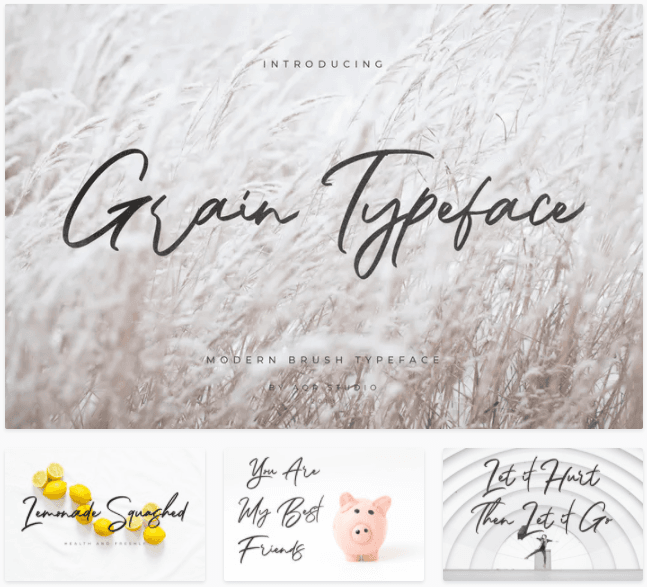
Зерно Typeface, который содержит строчный, верхний регистр, символ, а также поддерживает многоязычные. В этом шрифте много лигатуры. Зерно Typeface также поставляется с лигатур, стилистические чередующиеся и многое другое. этот шрифт подходит для моды, брендинга, каталога и другого дизайна, что вы хотите.